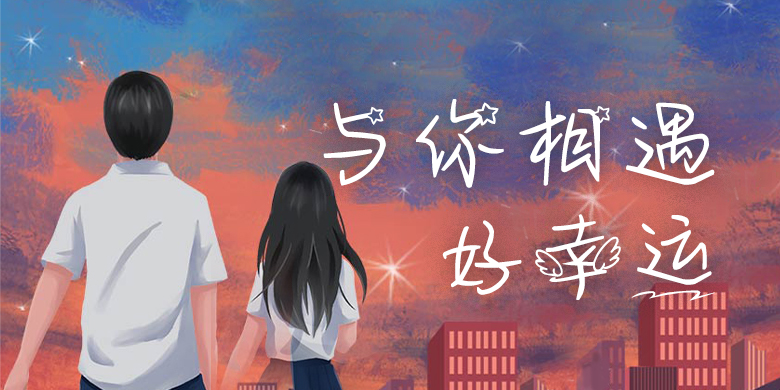
方正手迹-与你相遇好幸运
方正手迹-与你相遇好幸运,这款字体结构工整、笔画清晰,兼顾美观与易读性,适用于标题、正文、海报、包装、LOGO 等多种场景。字形优雅稳定,风格百搭耐看,适配日常排版与创意设计,让文字呈现更舒适、更具质感。方正手迹-与你相遇好幸运一笔一画,皆是细节,以均衡的比例、流畅的线条打造舒适视觉体验,字形端正大气,风格简约现代。无论是商业设计、品牌宣传还是日常排版,都能轻松驾驭,让文字更有格调与力量。方正手迹-与你相遇好幸运字体下载。
与你相遇好幸运是一款充满欢喜欢的字体,正如字体名称所传达的,幸运地相遇之后是心底温暖的欢喜。该字在结字上不拘法度,任由笔端自由流淌,使得该字气韵统却又不失其洒脱本性。再加上一些小挂件的点缀,使得该字更加趣味十足。适用于现代诗歌、短文的排版以及文化、商业类品牌的广告语设计。